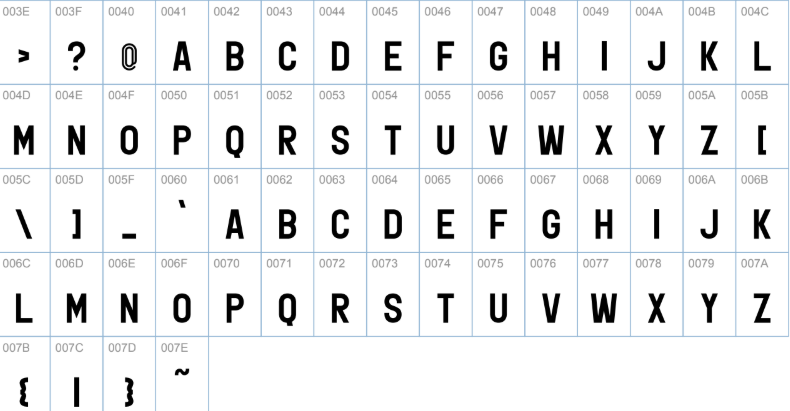
A temporada 2025/26 é um marco para o Esporte Clube Vitória, e a identidade visual dos uniformes reflete a força e a tradição do “Leão da Barra”. Em continuidade à parceria com a Volt Sport, os novos mantos trazem não apenas inovação tecnológica nos tecidos, mas também uma tipografia exclusiva que complementa o design das clássicas listras rubro-negras e do uniforme reserva.
Para designers gráficos, editores de jogos (como eFootball e FIFA) e criadores de conteúdo esportivo, utilizar a fonte correta é o detalhe que separa um trabalho amador de um profissional. A numeração e os nomes nas costas das camisas possuem um papel crucial na estética do uniforme, garantindo legibilidade e estilo dentro e fora do Barradão.
Neste post, disponibilizamos a fonte Vitoria 2025 – 26, uma recriação de alta fidelidade inspirada na tipografia utilizada pelos jogadores nas competições oficiais desta temporada.
Estilo visual da tipografia
A tipografia desenvolvida para a temporada 2025/26 do Vitória segue a linguagem visual moderna adotada pela Volt Sport.
- Estética: A fonte apresenta um design geométrico e robusto, transmitindo a solidez defensiva e a agressividade do ataque rubro-negro. Os caracteres possuem espessura média a grossa (bold), o que facilita a visualização à distância e nas transmissões de TV.
- Aplicação:
- Uniforme 1 (Home): Geralmente aplicada na cor branca ou dourada sobre as listras vermelhas e pretas, garantindo contraste.
- Uniforme 2 (Away): Aplicada em vermelho ou preto sobre a base branca da camisa.
- Personalidade: Ao contrário de fontes genéricas, esta tipografia possui cortes e ângulos sutis que se alinham à modernização da marca do clube, sem perder a essência clássica do futebol nordestino.